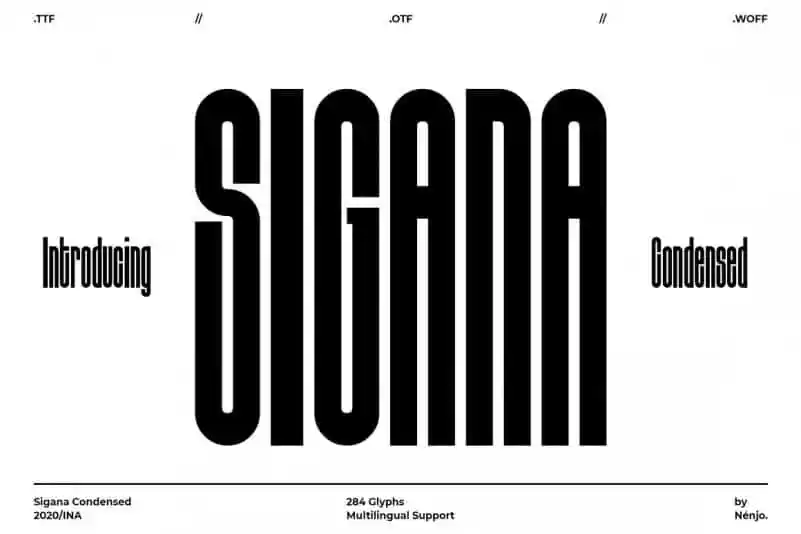
Sigana Display Font – Download Grátis
A fonte Sigana Display é uma sans serif que oferece um visual elegante e minimalista para qualquer projeto de design. Ela foi criada pelo font designer nénjo, especialmente projetada para aplicações visuais onde a atenção deve ser capturada. Com sua forma alta e simples, Sigana Condensed traz um ar moderno e elegante às criações digitais. Ideal tanto para o branding e as marcasos de título quanto para materiais de registro ou texto do corpo, esta fonte é uma ótima escolha para qualquer projeto que busque um equilíbrio entre simplicidade e sofisticação. Sigana Display é perfeita para quem busca uma alternativa moderna às fonts tradicionais, capaz de destacar a identidade visual em ambientes de design premium, elegantes e luxuosos. Seja você designer ou profissional do setor que busque um toque único, Sigana Display certamente atenderá suas expectativas.